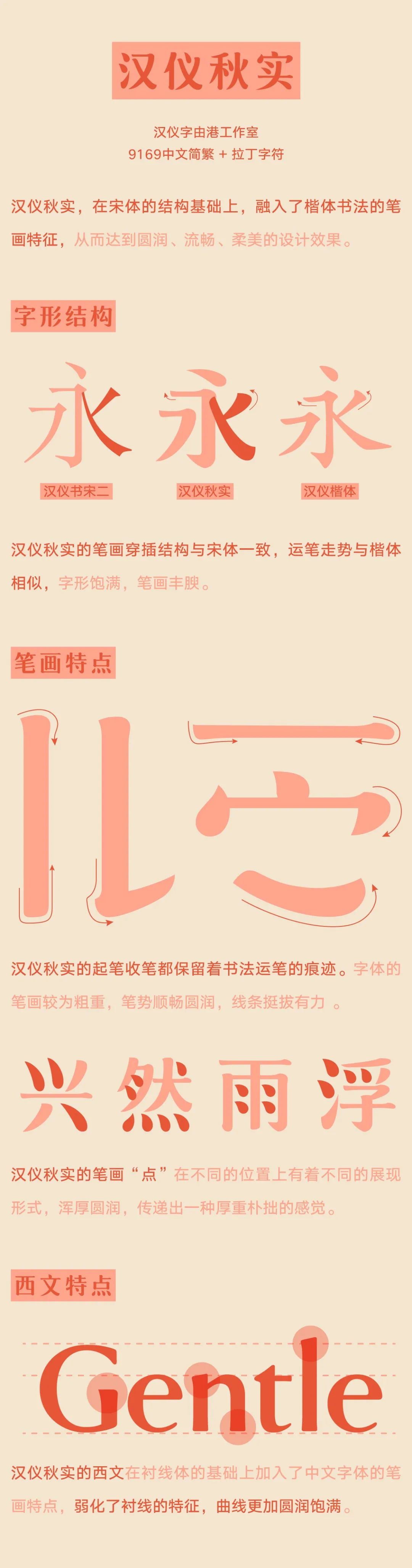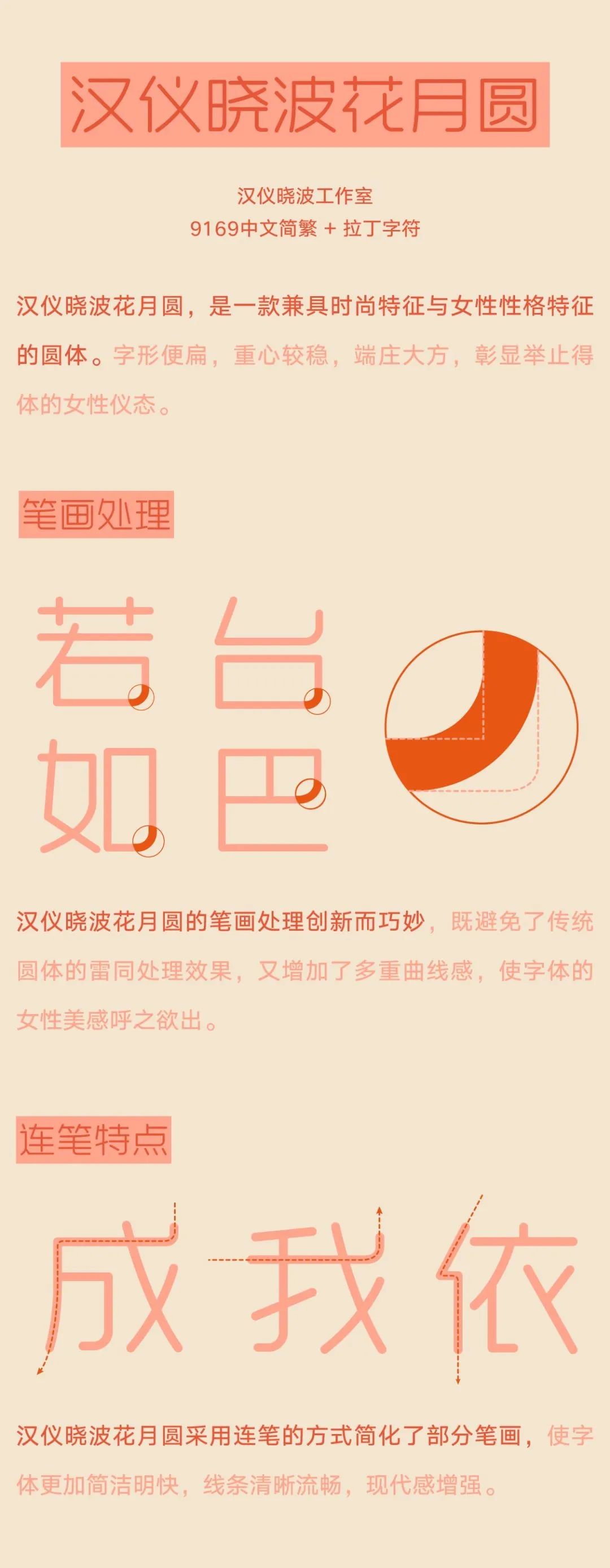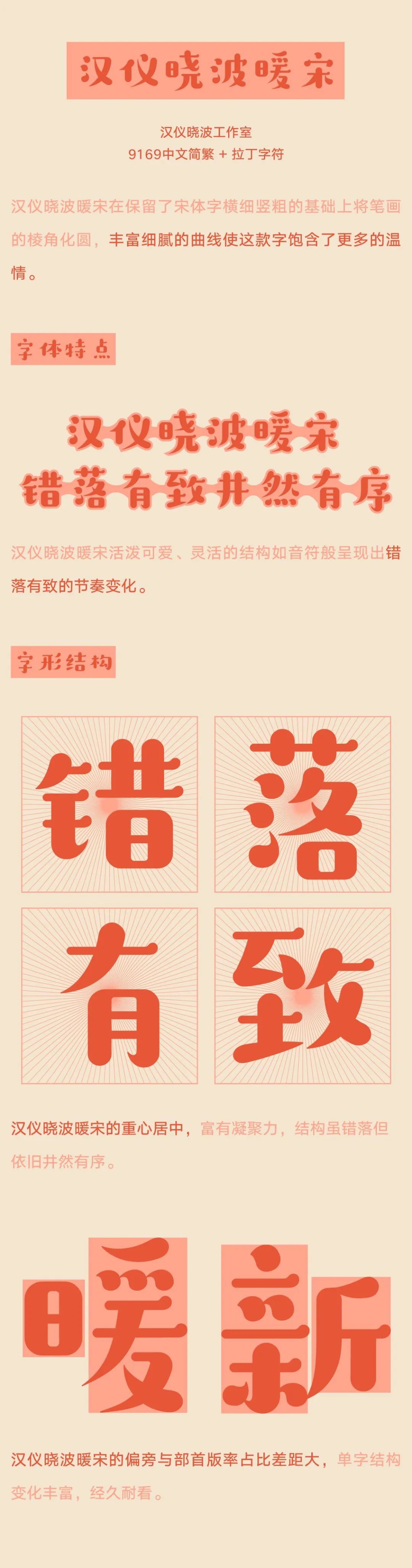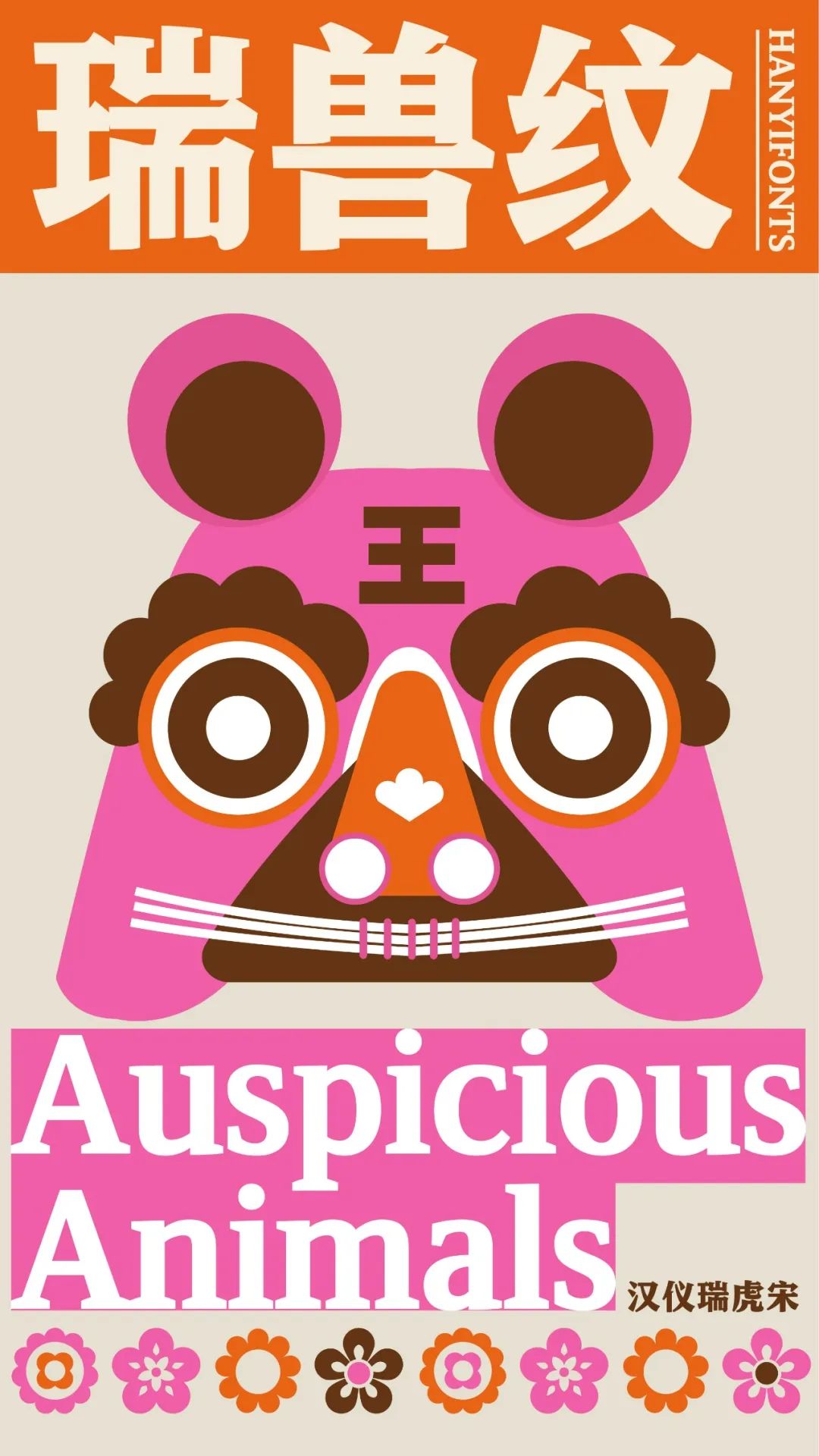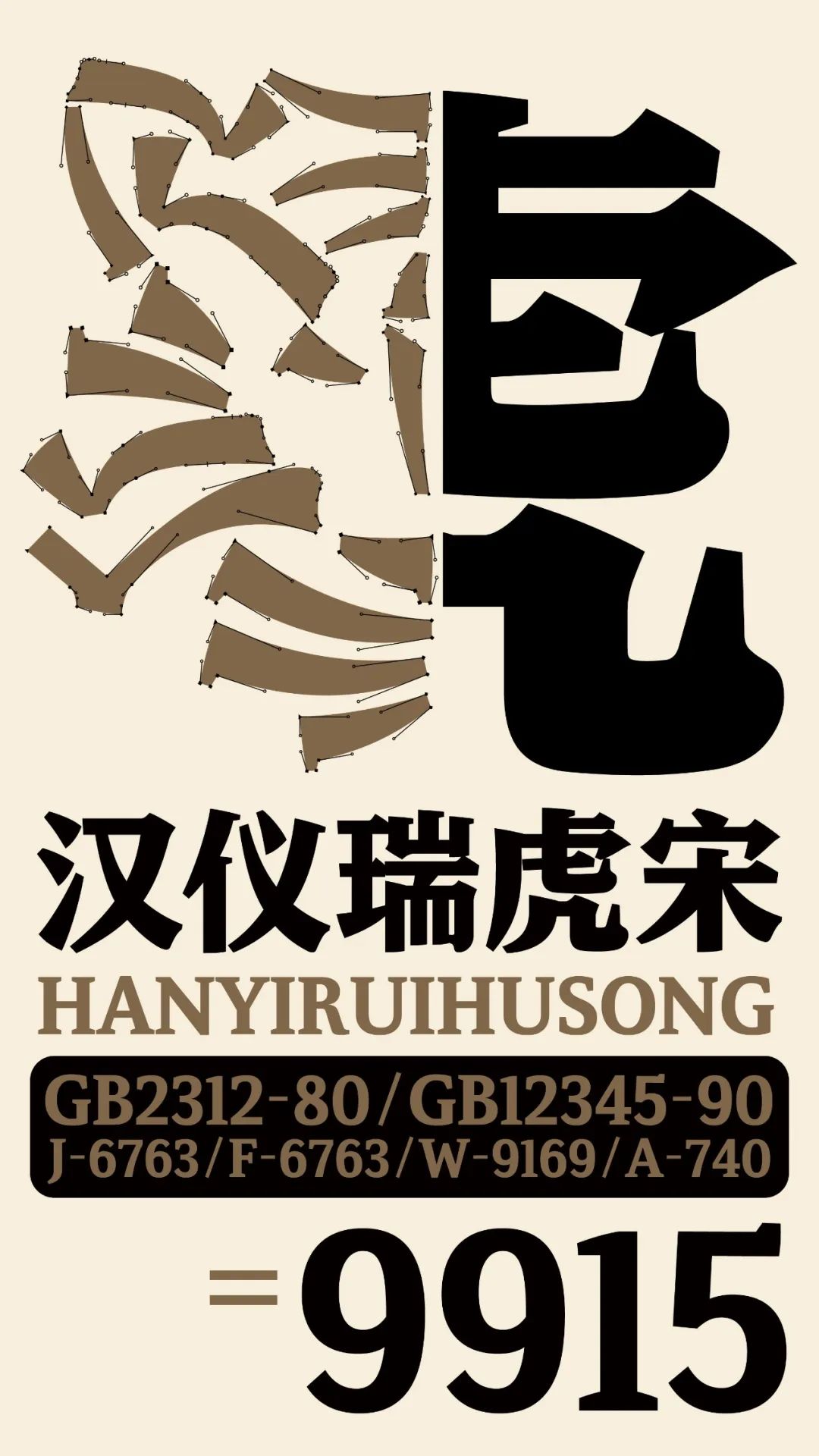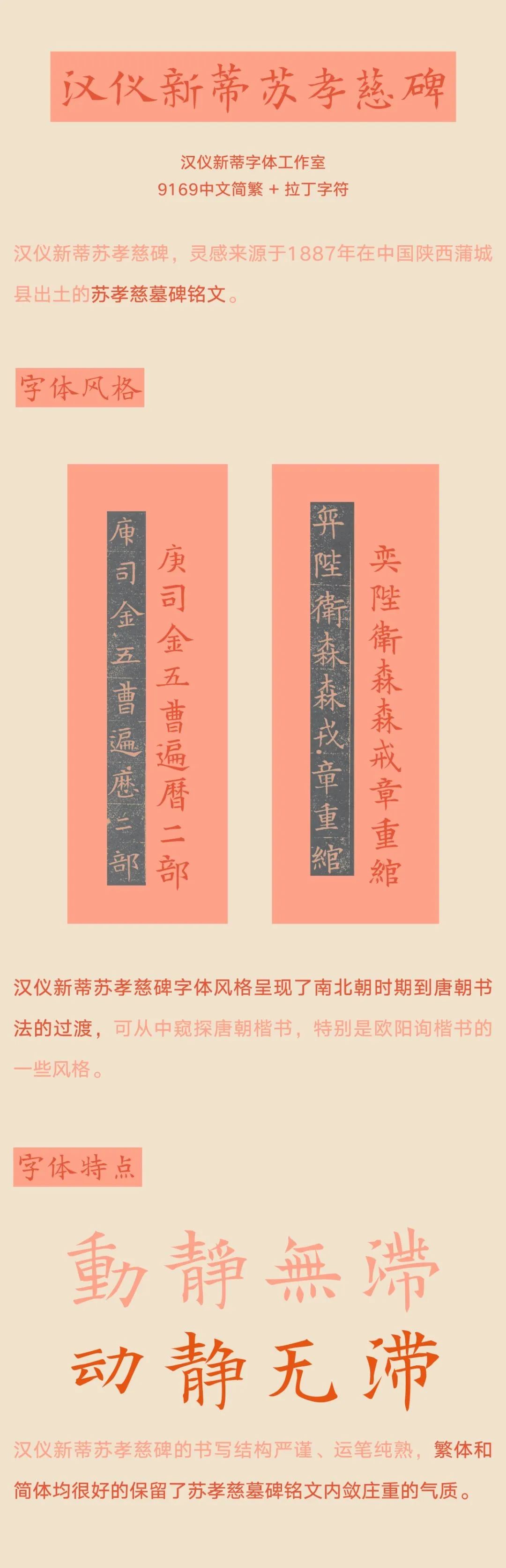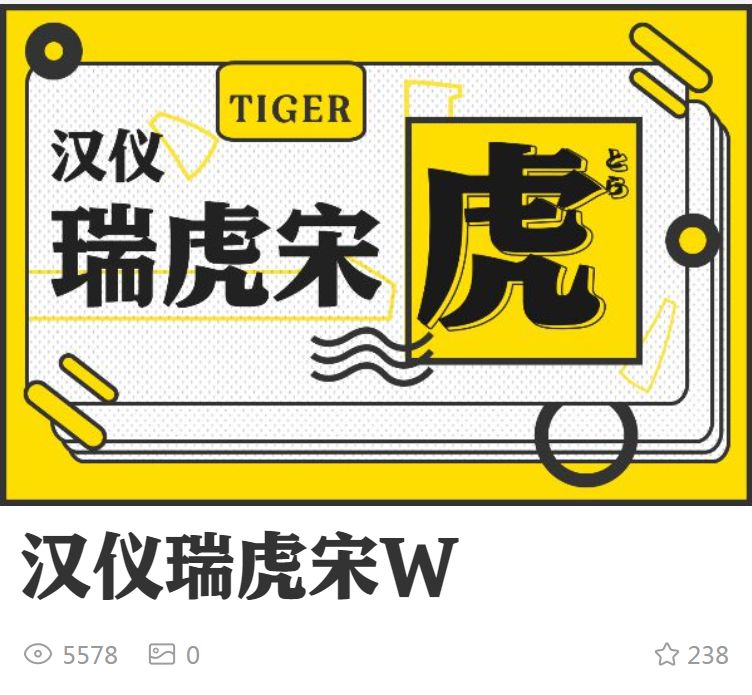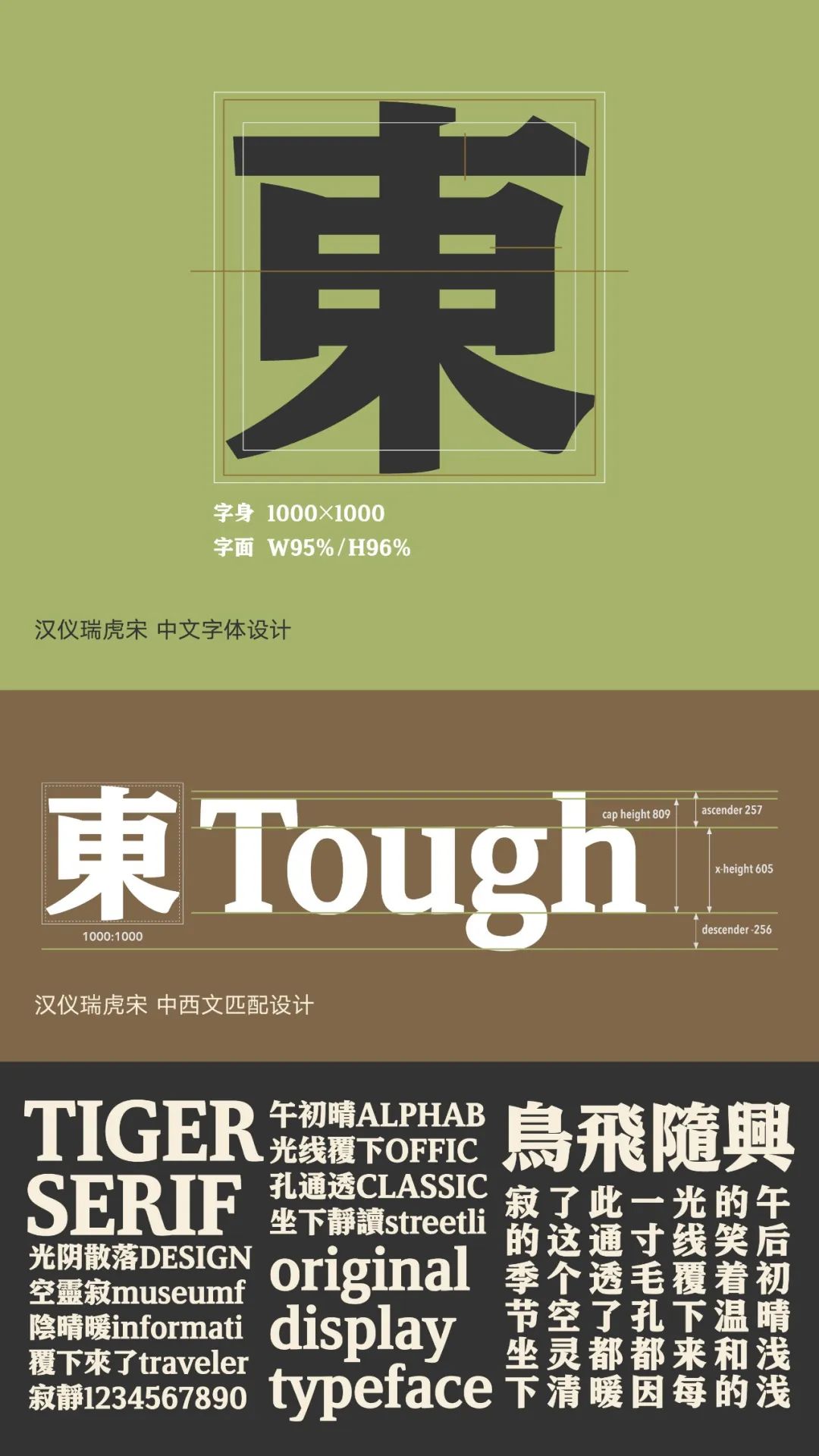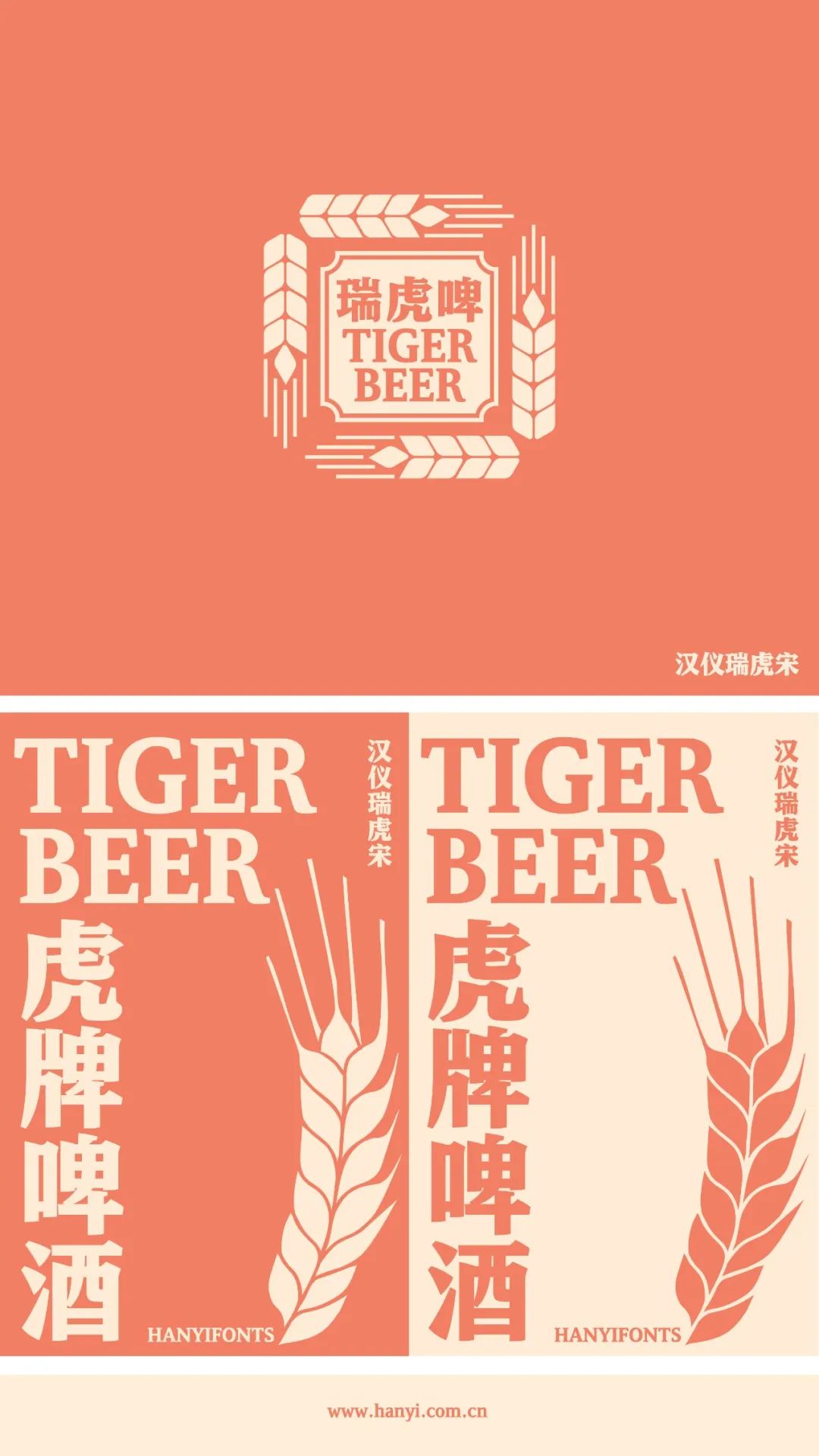
汉仪秋实
3月既是字由的生日,也是女人的节日,所以温柔亲和的字体必不可少,首先就是汉仪秋实。
汉仪晓波暖宋
汉仪晓波系列,之前出过很多爆款字体,像汉仪晓波美妍体、汉仪晓波折纸体、汉仪晓波画报黑等。
这次又带来了两款新字,一款是看起来就很酥的汉仪晓波暖宋~
汉仪晓波花月圆
另一款是汉仪晓波花月圆,笔画偏细,很适合用在时尚感的设计中。
汉仪新蒂苏孝慈碑
汉仪新蒂系列的字体,字由上足足有24款,有古风的汉仪新蒂唐朝体、卡通的汉仪新蒂黑板报、也有手写的汉仪新蒂下午茶。
这次新上的是汉仪新蒂苏孝慈碑,灵感源自1887年出土的苏孝慈墓碑铭文。
汉仪瑞虎宋
前面说的都是女性字体,最后来一个霸气的男性字,那就是战国栋老师继“汉仪瑞意宋”之后的又一力作——汉仪瑞虎宋(嗷呜)。
同样是宋体字,但不同于汉仪瑞意宋高挑、时尚的气质。
汉仪瑞虎宋则是一种厚重、强大的霸气全开,就像字体名字的“虎”一样。